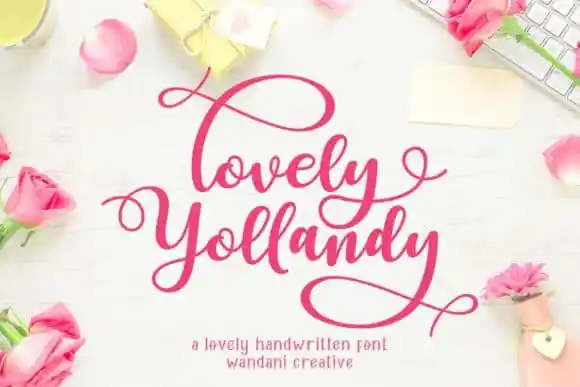
Lovely Yollandy Calligraphy Font – Fonte Grátis
Lovely Yollandy Calligraphy Font
Lovely Yollandy é uma elegante fóntica calligráfica que combina delicadeza com frescura amena. Com caracteres bem equilibrados e encantadores, esta fonte se adequa a um amplo leque de ideias gráficas. Ela foi criada por Beautypes, uma font designer famosa em 99designs. Esta fóntica é perfeita para aqueles projetos de design inusitados e criativos. “Lovely Yollandy” é uma indispensável adição para qualquer trabalho gráfico. Este estilo script atende a um amplo leque de aplicações, incluindo cartões de cumprimentos, identidade visual, design de estação de trabalho, redes sociais, convites para casamento, layouts de revistas e impressão em massa.